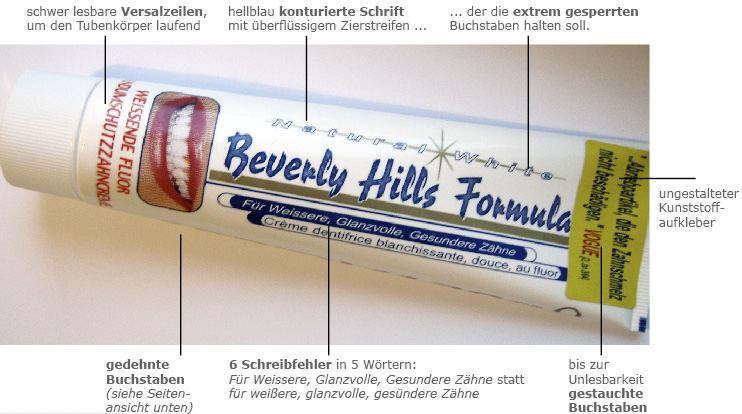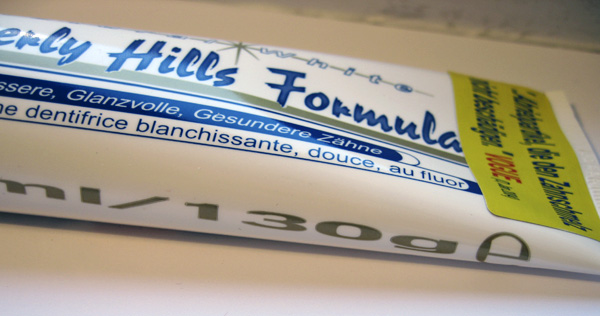
Typografen kriegen stumpfe Zaehne ...... wenn sie diese Zahncremetube betrachten. Ist mir heute morgen im
Badezimmer in die Hände gefallen: Beverly Hills Formula, aus den
irischen Purity
Laboraties. Selten bekommt man eine Produkt in die Hand, dessen
Verpackung alle typografischen Kardinalsünden auf sich vereint. Die muss
![]() Wenn bei der Gestaltung der Beverly-Hills-Zahncremetube eine professionelle
Designagentur im Spiel war, so lautet unsere Empfehlung: umgehend getrennte Wege
gehen. Lasst Euch nicht verar...